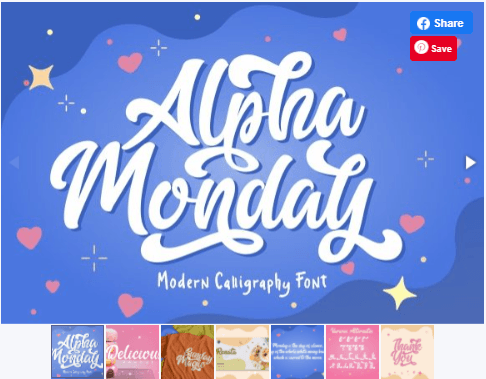
Alpha Monday Font
Alpha Monday - это свежий и крутой рукописный шрифт. Добавьте его к своим самым креативным идеям и обратите внимание, как они оживают!